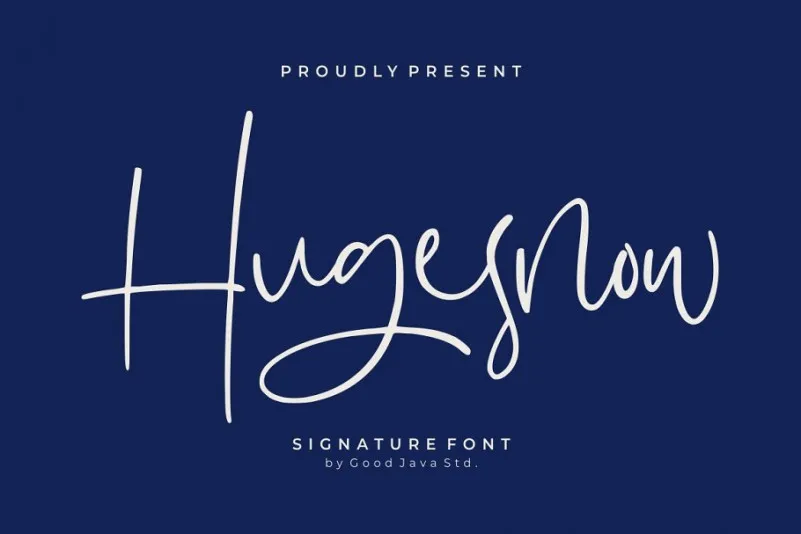
Hugesnow Signature Font – Download Grátis
Agora estamos lançando Hugesnow Signature Font, uma nova fonte script que adiciona um toque autêntico ao seu design. Seu estilo é natural e moderno, sendo perfeito para uma variedade de aplicativos como logotipos, convites, embalagens de produto, rótulos, publicidade, conteúdo nas redes sociais, água-marinha, eventos especiais ou qualquer outro projeto que você queira dar um toque especial. Com seu estilo de escrita artesanal e sua estrutura elegante, Hugesnow Font dá um tom autêntico às suas criações. É perfeito para dar um toque pessoal a seus trabalhos finais. Este é o tipo certo para aqueles que procuram uma fonte de estilo próprio para seu próximo projeto gráfico.